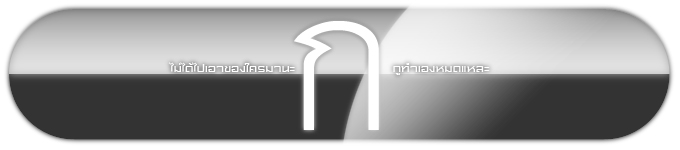
เอาฟอนต์เว็บนี้ไปใช้หลายทีแล้ว
ที่ใช้หลัก ๆ ก็ของห้าโอ ใช้ทำเฮดบล็อก
ของป๋าเลย์เพื่อนนี่ใช้เป็นดิสเพลย์บ่อยมากเลยเอามารวบซะ
อย่าลืมใช้ฟอนต์ใหม่ตูด้วยนะ (ถ้าทำเสร็จ  :08:)
ป.ล. เจออีกแล้ว แต่ตูไม่ได้ทำ
มีใครบอกรึยัง
ได้ข่าวว่าไอ้ตัวอักษรพวกนั้นกำลังจะถูกรื้อน่ะ
เก็บไว้ให้พี่ห้าโอเค้าระลึกความหลังครั้งสุดท้ายก่อนโดนรื้อน่ะ
ฟอนต์นั้นห่วยมากครับ
คาดว่าก่อนสิ้นปี 50 คงจะได้แก้ทั้งขบวน
head ก.ไก่ น่ะ
ตัวเล็กๆ นั่นฟอนต์อะไรคะ  :09:
SP-Armageddon จ้ะ
ทำไมหรอ สวยใช่มั้ยล่ะ  :26:
สวยค่ะ  :12:
แนะนำ ลลพ ใช้ Norasi หรือฟอนต์คล้ายๆ Angsana สิ  :42: